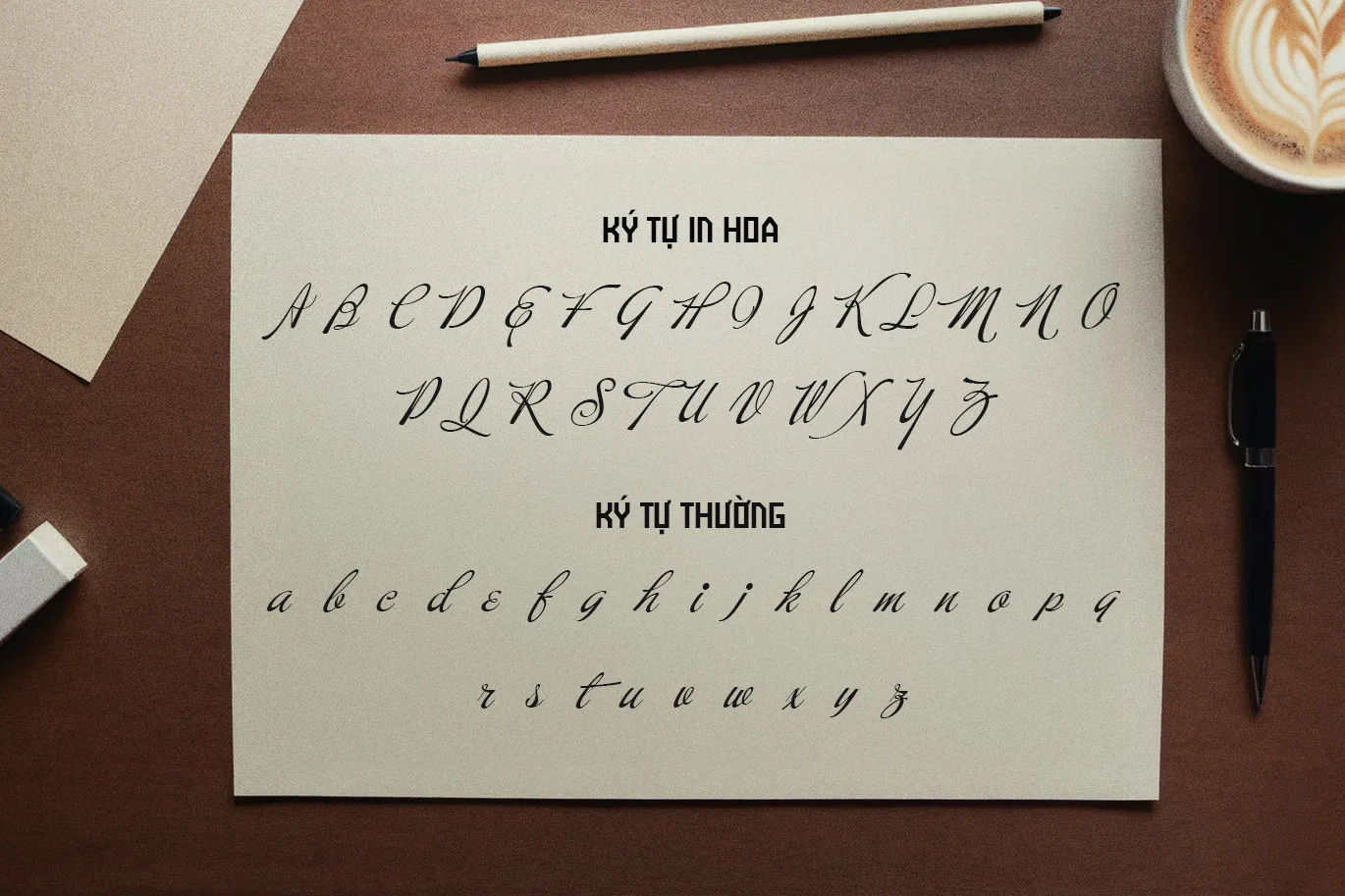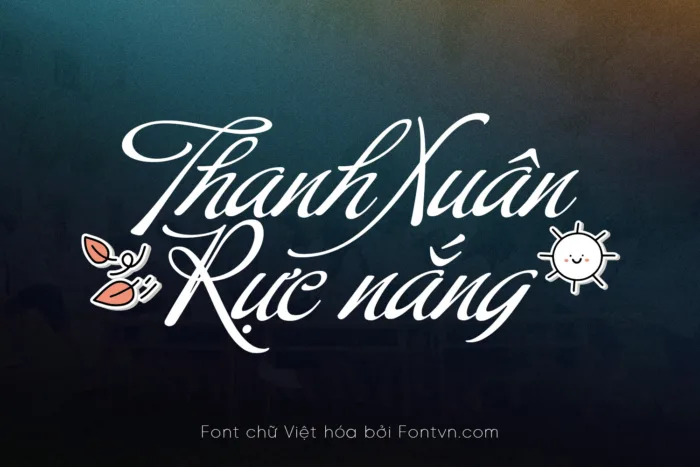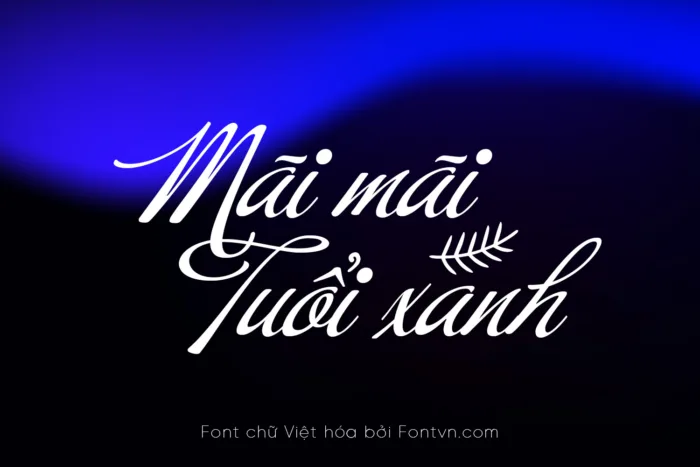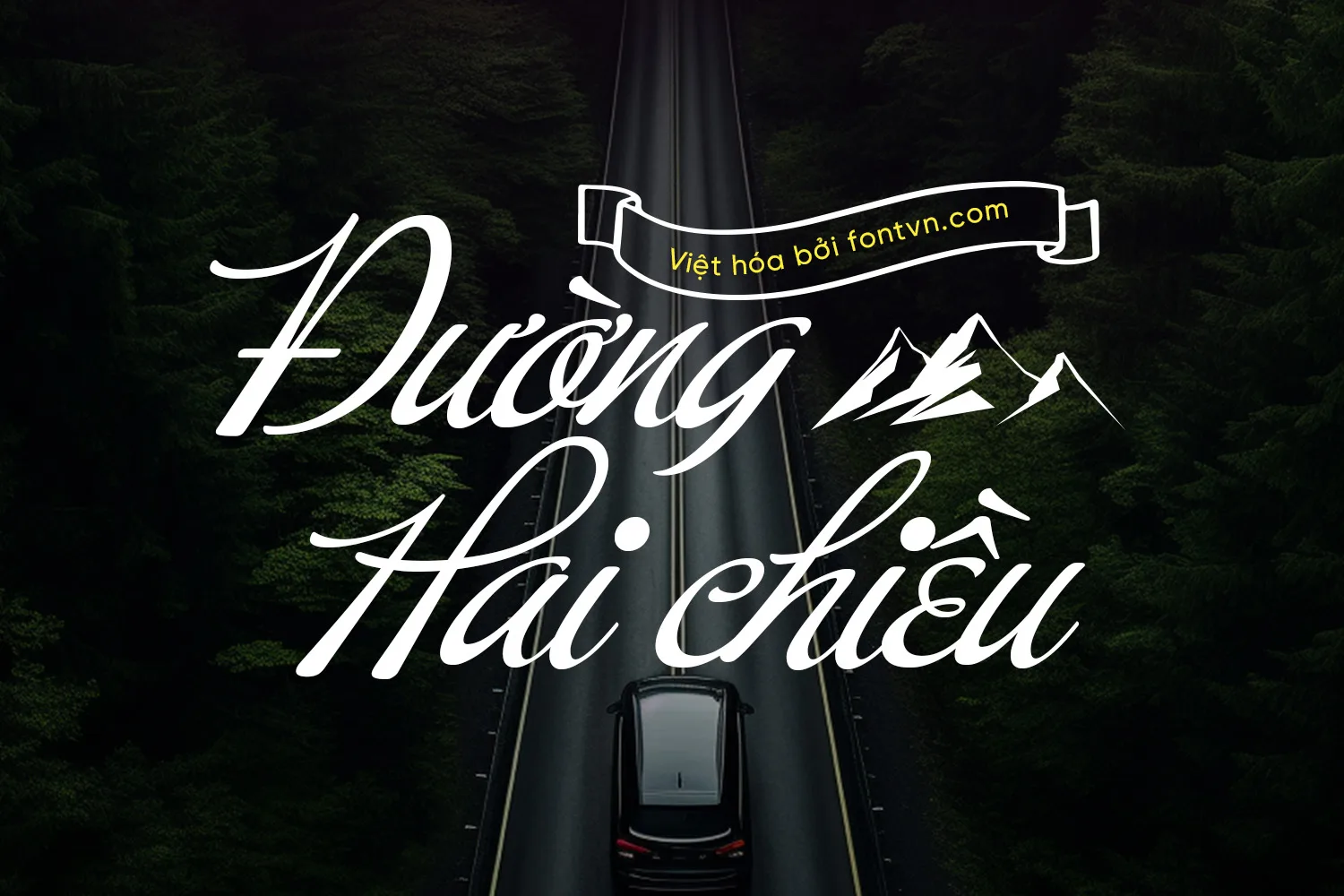
DVN Buffet Script – Font Việt hóa với nét chữ uốn lượn thanh thoát và cực kỳ tinh tế
DVN Buffet Script Việt hóa là một kiểu chữ tay bay bướm mang phong cách cổ điển pha lẫn sự hiện đại tinh tế. Những nét cong uốn lượn mềm mại, đường lối thanh mảnh nhưng dứt khoát tạo nên một cảm giác sang trọng, lãng mạn và nghệ thuật. Font cực kỳ phù hợp cho các thiết kế logo thời trang, bìa thiệp cưới, tiêu đề poster hay branding mang đậm dấu ấn cá nhân. Phiên bản Việt hóa được tối ưu đầy đủ dấu tiếng Việt giúp bạn thiết kế một cách hoàn hảo.